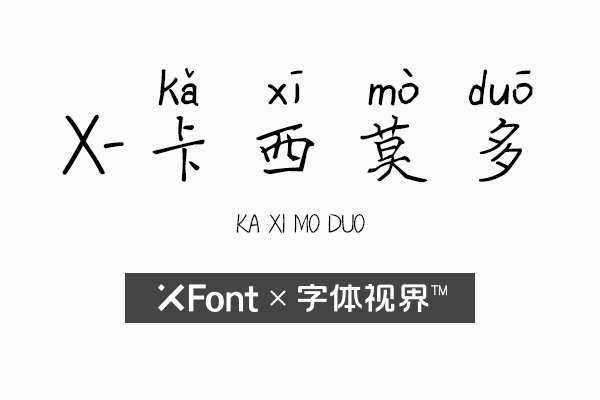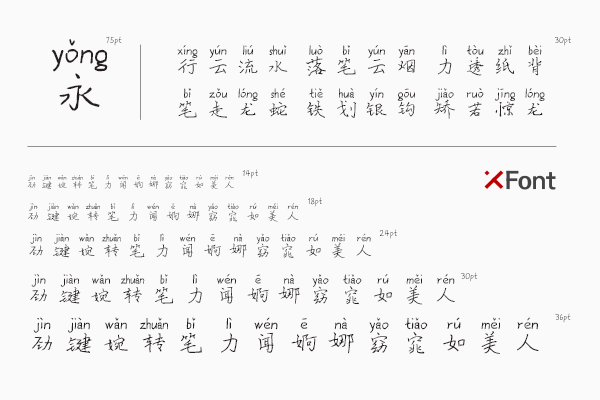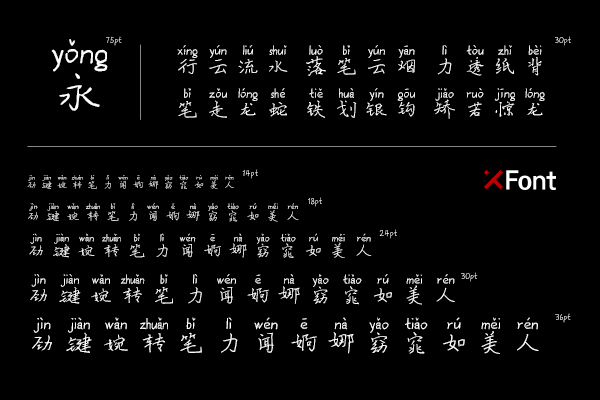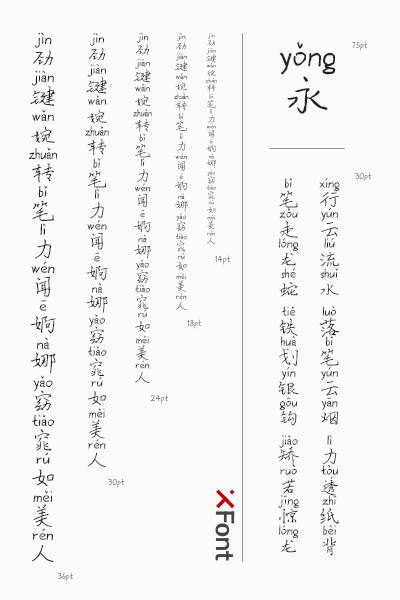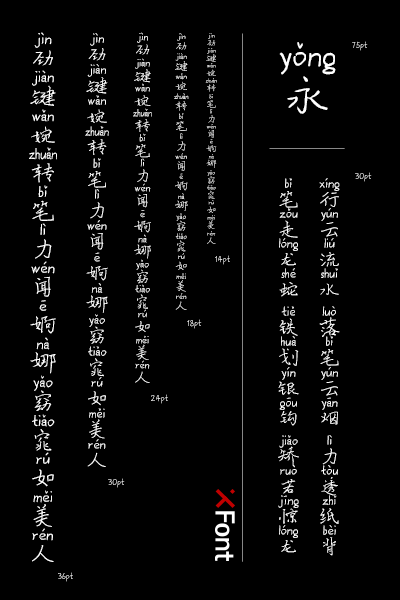
什么是XFont字体
XFont是主要通过手绘而获得的一种字体品牌,品牌中包含的字体形式众多,由于采用的设计年龄段不同,所以让品牌做出的手绘字体产生了明显的差异性,既有年轻人的活跃又有成年人的沉重稳重。
所谓一个种类繁多的字体品牌在设计中的使用非常众多,所以人们更加的喜欢选择,XFont-卡西莫多作为附属的一个字体受欢迎程度还是很高的。